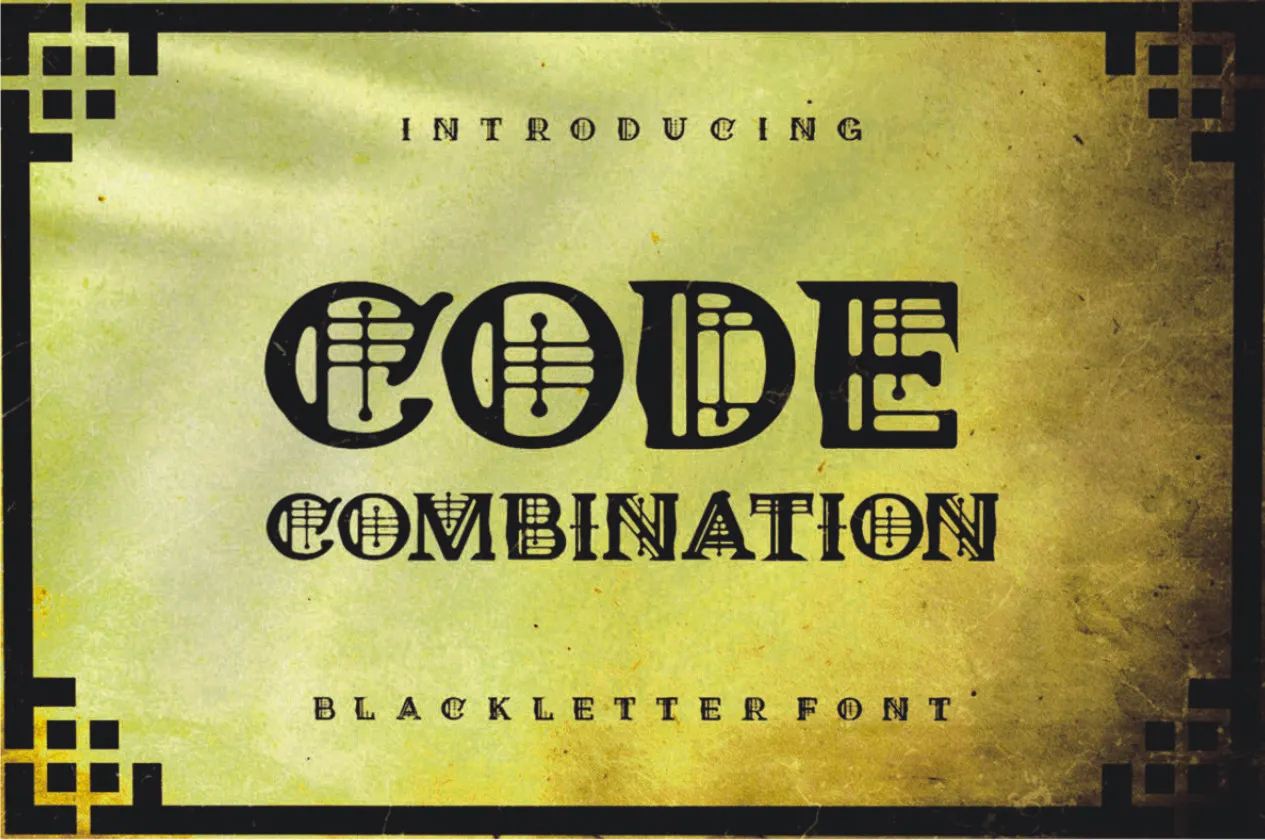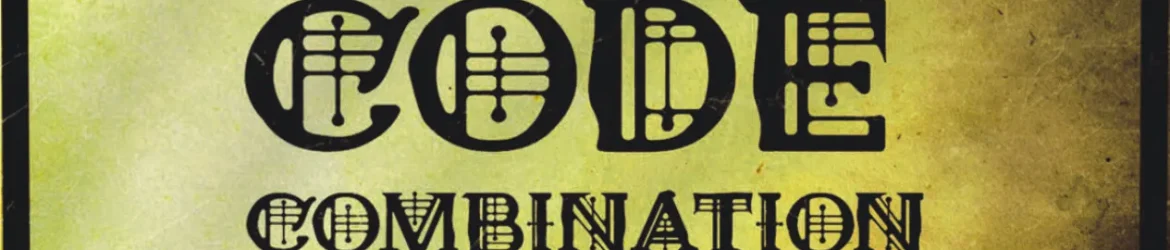
Code Combination Font – Download Grátis
Aqui está uma descrição para a página de download da fonte “Code Combination Font”, voltada para o público-alvo de designers e criativos amadores no Brasil: “Quer designers brasileiros, aqui há um novo amigo para seu portfólio! Este é o Code Combination Font – uma combinação única de letras Blackletter que traz a essência da serifada de volta às suas criações. Não importa qual seja o tema do seu trabalho, este font tem potencial para transformar até mesmo as mais simples ideias em verdadeiros trabalhos de arte. Agora você pode ter um recurso gráfico inigualável na sua coleção de fonts que se destaca dos demais. Seja o próximo design da moda ou a próxima tendência na revista especializada, este Blackletter não vai decepcionar. Tente ele agora e veja o poder desta font em ação.” Este texto mantém a essência informativa e convidativa do blog de recursos gráficos, sem inventar características inexistentes e mantendo o tom recomendado.